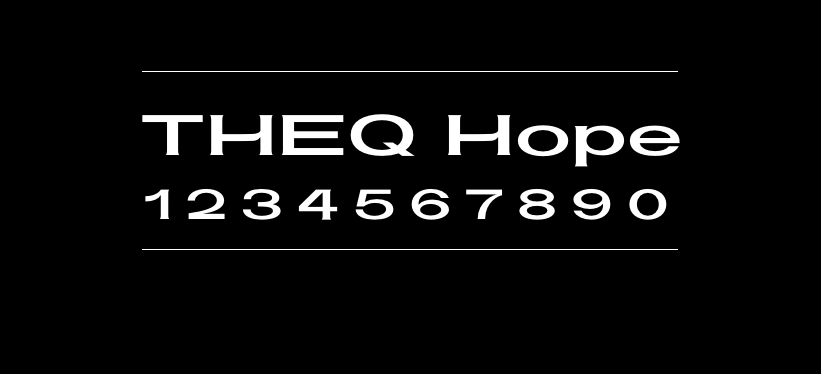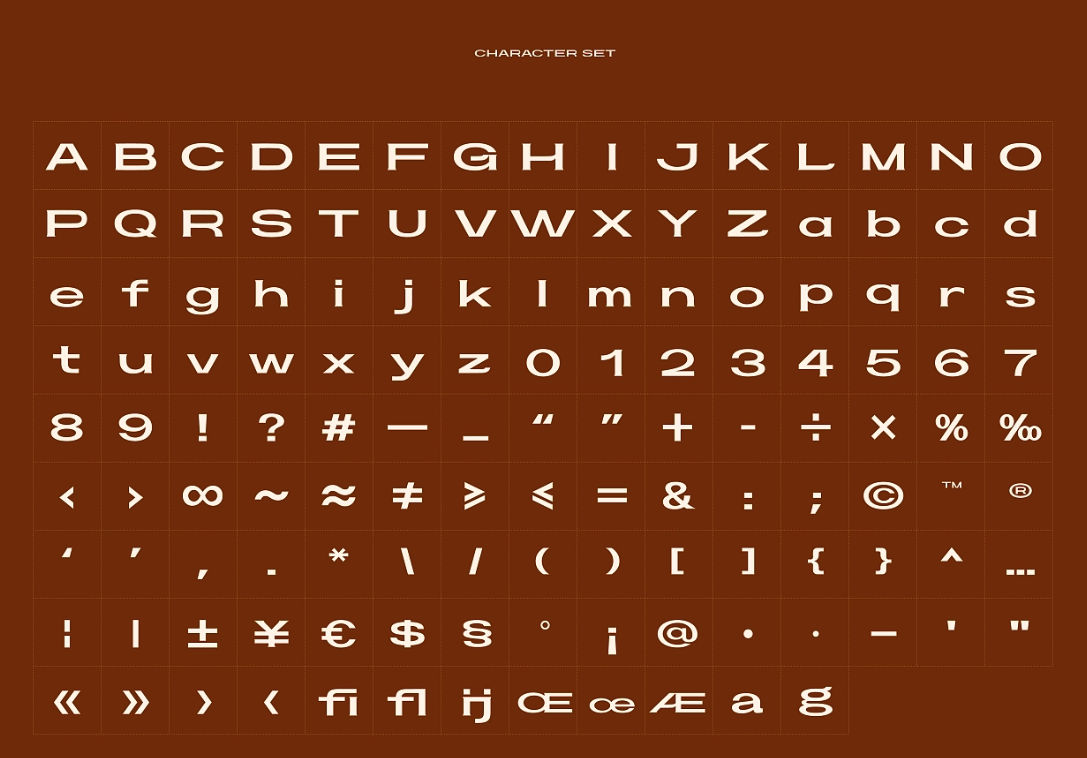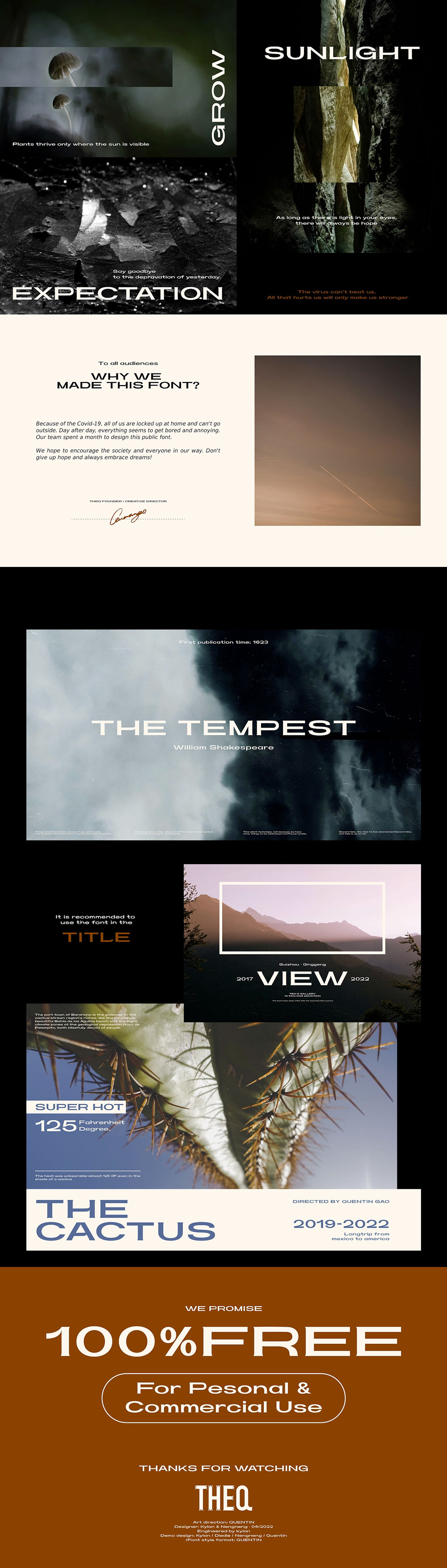
THEQ Hope
THEQ Hope 是上海的设计工作室THEQ在上海疫情期间创作的一款英文字体,于2022年5月发布,作者声明免费商用。
THEQ Hope 字形宽大稳重,适合标题、海报、电影、印刷等多种场合。
在上海的朋友们应该理解,这段时间过的真的很漫长,无尽的居家办公一度让THEQ的小伙伴们陷入焦虑,作为一家见证了许多新品牌诞生的设计工作室,我们非常明显地感受到:整个市场都慢了下来。凝滞的物流,未知的解封日期,资金的压力,以及疫情对消费者心智可能带来的影响……都成了曾经踌躇满志的创业者们的一道道枷锁。
但是,焦虑过后,THEQ也在思考:我们为什么选择做设计,在当下的语境中,设计又可以为大家做什么?
我们认为: 选择设计作为事业是因为专业与热爱,而设计本身则是一种经过深思熟虑的传达。在当下,THEQ真诚希望能以力所能及之事,不耽于无谓的抱怨与迷茫,为愿意交流或者需要帮助的同行、品牌主们,带来一些设计上的支持。并且,是以免费的公益形式。这,是身处疫情之中的THEQ回馈社会的一些小小责任感。
于是,经过THEQ「字作人」们连续一个多月的努力,我们的首款免费字体“THEQ Hope”今天正式发布。
这款英文字体的名称为“Hope“,顾名思义就是希望的意思,我们希望无论在任何艰难的情况下都能够对未来保持信心,坚守理想与信念,苦难终究会过去,风雨后彩虹现,永远保持乐观积极向上的精神。
在字体方面,从一开始这款字体就是定位标题字体,经过我们的多轮测试,也的确更适合在标题中去使用,未来我们也会开发一些适应性更广泛的中英文字体,敬请期待吧~
这是我们第一次出品字体,因为时间的关系,依然有很多的不足和待调整的地方,我们也会承诺在以后的日子里提高我们字库的设计水准,在公益性和专业性两方面都达到一个良好的平衡。